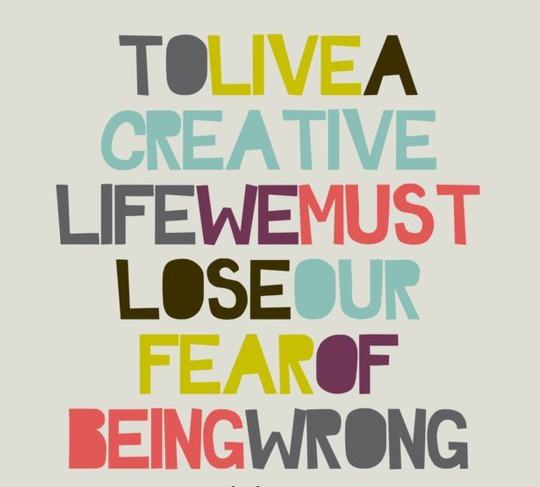
Wie heisst diese Schrift?
auf meinem Rechner gibt es einen Ordner namens Typo-Inspo - dort landen Screenshots von Schriften, die mir gut gefallen. Bei neuen Projekten wird wild darin herumgekramt und manchmal finde ich tatsächlich etwas, was zur aktuellen Aufgabe passt wie die Faust aufs Auge :)  Leider steht natürlich nicht bei jeder Schrift dabei, wie das gute Stück heisst *ach wie wäre das schön!*
Aber vielleicht könnt ihr mir weiterhelfen? Kennt jemand diese Schrift? Seh sie öfter, aber kenne leider den Namen nicht. Würde mich notfalls auch mit einer sehr ähnlichen begnügen,aber wenn 100 % möglich sind, natürlich am Liebsten GENAU diese :)
Ich glaube, der Vorschlag ist mir aber etwas zu "wild" ;)
Danke Norbert, die ist schon mal eine gute Möglichkeit, falls das Original weiter verstecken spielt!  :nicken:
ich würde jetzt nicht ausschließen das die selbst gemacht ist, oder?
Schau doch mal bei House Industries die haben ein Paar coole Vertreter dieser Art »schrabbeligen« Display-Fonts. Andernfalls, schonmal bei dafont oder fontsquirrel geschaut?
Die könnte zum Beispiel schon einmal passen.
Das ist handmade von Amanda Cherie. Was aber nicht heißt, dass kein Font zugrunde lag ;-) Aber du könntest sie bei facebook fragen.
Die Londrina bekommt auf jeden Fall eine Chance - und Danke für die Auflösung, Bertel, vielleicht probiere ich es auch mal selbst ganz analog ;)